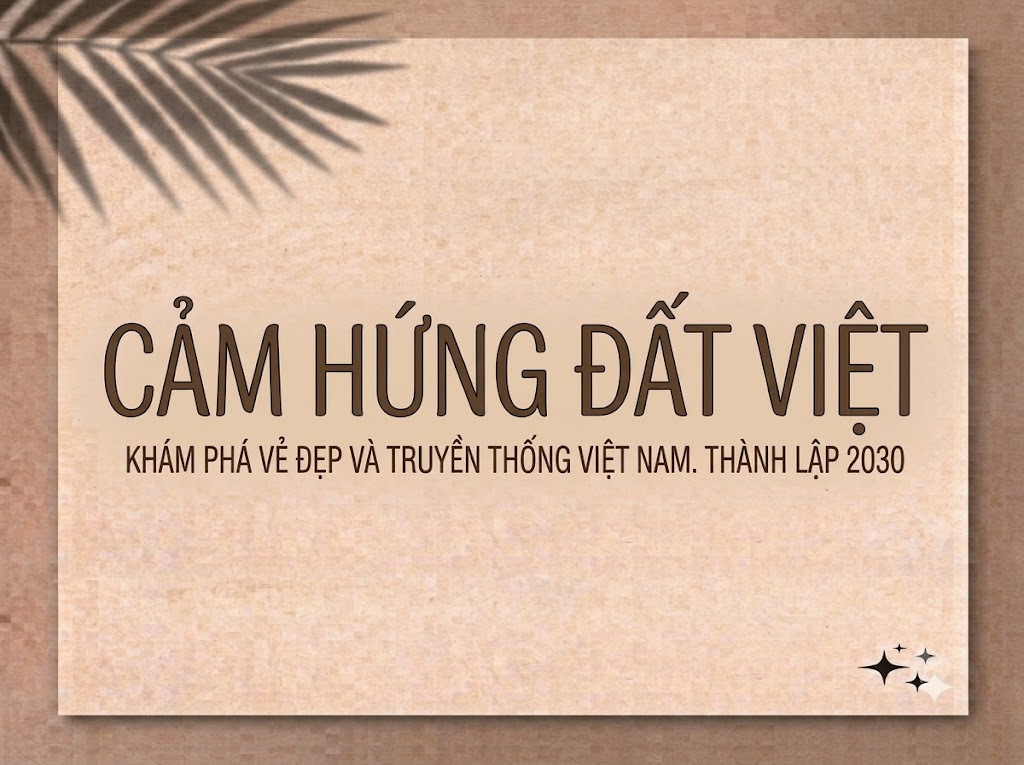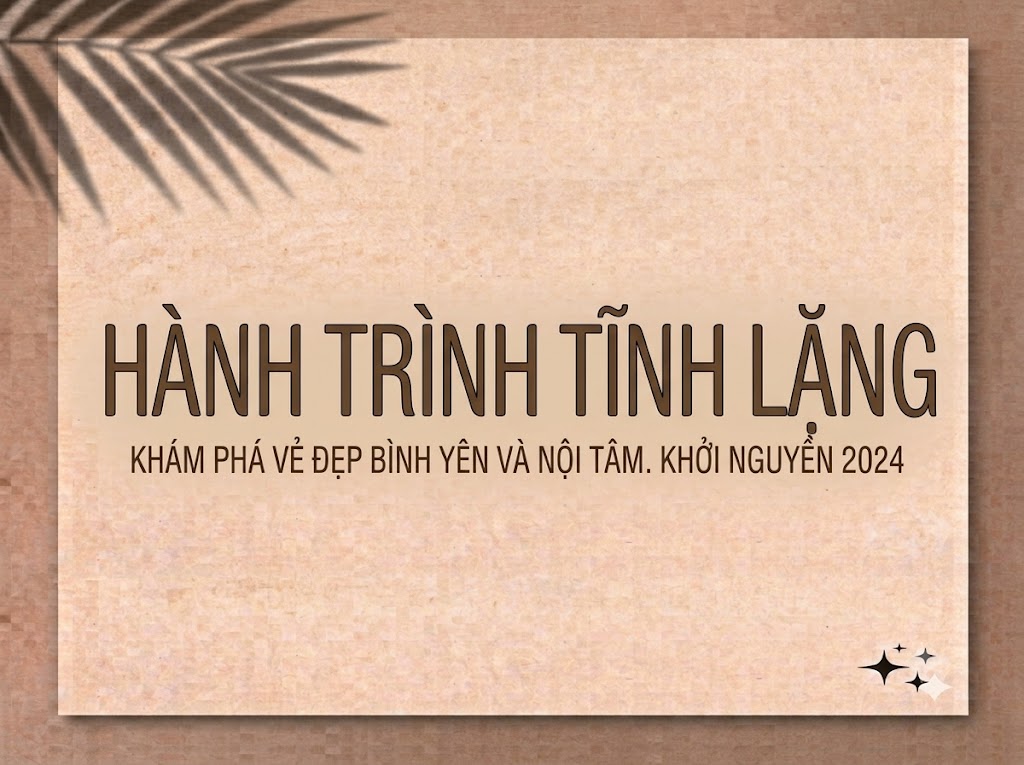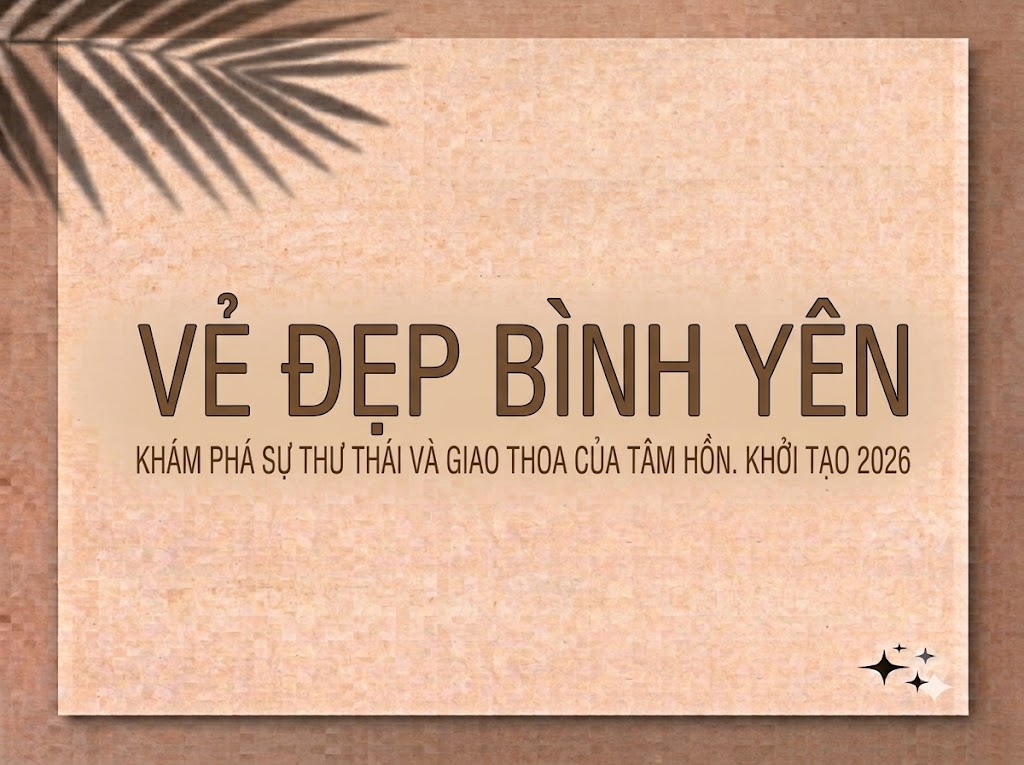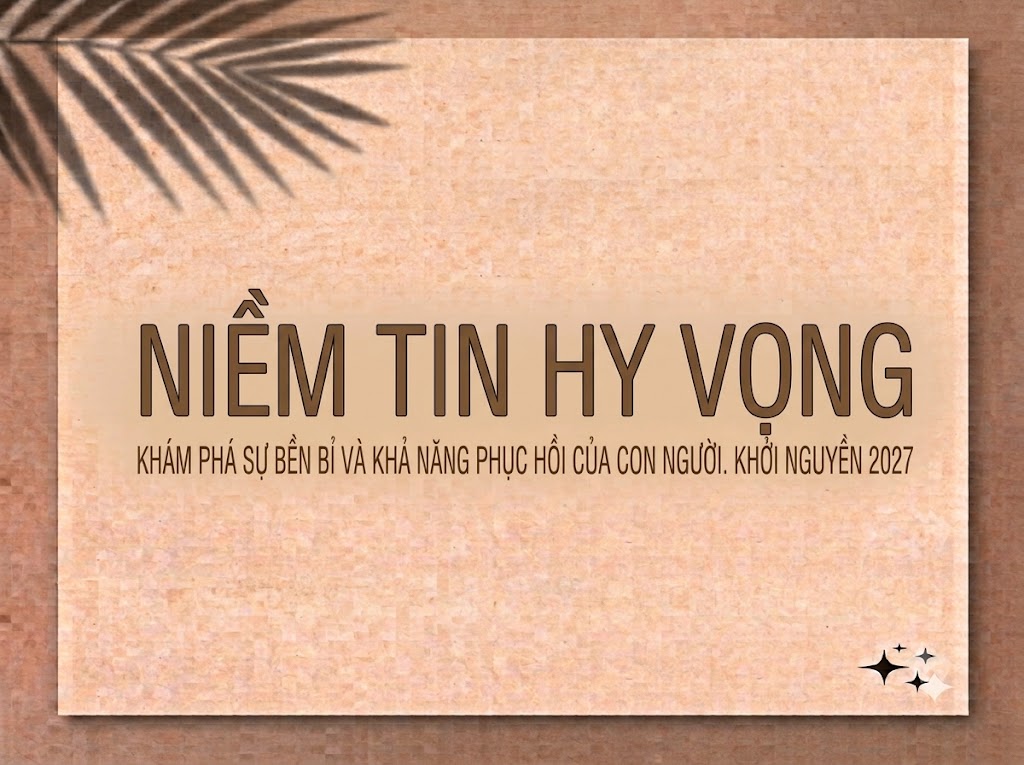
1FTV SS Magnetic
Trong thiết kế đồ họa hiện đại và sáng tạo nội dung số, việc lựa chọn một phông chữ không chân (sans-serif) tối giản nhưng có độ nhận diện cao luôn là yếu tố quyết định. Một phông chữ có cấu trúc hình học chuẩn mực, đường nét dứt khoát không chỉ giúp tối ưu hóa thị giác mà còn nâng cao trải nghiệm đọc của người xem trên các nền tảng di động.
Nếu bạn đang tìm kiếm một bộ font đa năng, mang tinh thần công nghệ, hiện đại và có khả năng hiển thị hoàn hảo từ các tiêu đề lớn đến phụ đề video ngắn, thì font 1FTV SS Magnetic chính là giải pháp không thể bỏ qua.
Giới thiệu về font 1FTV SS Magnetic
Font 1FTV SS Magnetic là một bộ chữ thuộc thể loại hiển thị không chân mang phong cách hình học đương đại (geometric sans-serif), hướng tới sự sạch sẽ, chuyên nghiệp và tối giản.
Nhờ cấu trúc kỹ thuật đồng bộ này, phông chữ có khả năng hiển thị vô cùng sắc nét trên các phần mềm đồ họa chuyên nghiệp mà không lo gặp phải lỗi răng cưa khi phóng lớn bố cục hay thiết kế các ấn phẩm khổ rộng.
Đặc điểm nổi bật của phong cách thiết kế SS Magnetic
Sức hút lớn nhất của font 1FTV SS Magnetic đến từ phom dáng đứng ngay ngắn, gọn gàng kết hợp với các tỷ lệ hình học cân đối và những đường vát cạnh vô cùng tinh tế:
Cấu trúc Geometric tối giản: Phông chữ sở hữu những đường bo tròn thông thoáng ở các ký tự như o, e, c, a, g, kết hợp với các nét thẳng vững chãi, tạo cảm giác vô cùng hiện đại và mang hơi hướng công nghệ.
Hỗ trợ hoa – thường đồng bộ: Bộ font hỗ trợ trọn vẹn cả hệ thống chữ cái viết hoa lẫn chữ viết thường, giúp các nhà thiết kế tự do sắp xếp bố cục nhằm mang lại một nhịp điệu đọc tự nhiên và thoáng mắt nhất cho người xem.
Độ dày nét vừa vặn (Medium/Bold): Nét chữ có độ dày lý tưởng, không quá thô cứng nhưng đủ sức nặng để làm nổi bật thông điệp truyền thông từ khoảng cách xa.
Để phông chữ vận hành hoàn hảo trên mọi hệ điều hành và phần mềm biên tập, phiên bản font 1FTV SS Magnetic đã trải qua quy trình xử lý thông số kỹ thuật nội tại vô cùng kỹ lưỡng:
Hệ thống khoảng cách chữ (kerning) và độ giãn dòng (tracking) đã được căn chỉnh chuẩn xác, giúp văn bản khi đứng cạnh nhau luôn đạt tỷ lệ vàng về mặt khoảng trống, không bị dính nét hay gây ngột ngạt cho người đọc.
Tích hợp đầy đủ dãy số từ 0-9 cùng hệ thống ký tự đặc biệt, dấu câu thông dụng (
Bản Việt hóa chuẩn chỉnh này đảm bảo các nhà sáng tạo có thể gõ nội dung tiếng Việt hoàn toàn mượt mà, tự nhiên mà không lo gặp phải tình trạng nhảy font hay lỗi hiển thị dấu câu khó chịu.
Hình ảnh demo thực tế của font 1FTV SS Magnetic
Kích thước nhỏ (12pt – 24pt): Nhờ cấu trúc chữ đứng ngay ngắn và khoảng hở chữ thông thoáng, các khối chữ viết thường vẫn hiển thị cực kỳ rõ ràng, sắc nét và dễ đọc ngay cả trên màn hình điện thoại di động cỡ nhỏ.
Kích thước lớn (36pt – 72pt): Đây là đất diễn lý tưởng nhất để font chữ phô diễn toàn bộ sự hiện đại, tạo hiệu ứng thị giác chuyên nghiệp, gọn gàng và ngăn nắp cho các dòng headline chính.
Ứng dụng của font SS Magnetic trong thiết kế đồ họa và làm video
Sở hữu nét cá tính thanh lịch, hiện đại và cấu trúc hoa – thường linh hoạt, font 1FTV SS Magnetic mở ra không gian ứng dụng vô cùng rộng lớn cho các dự án truyền thông và marketing hiện đại:
Làm tiêu đề và phụ đề video ngắn (TikTok, Reels, Shorts): Dáng chữ đứng, gọn gàng và thanh thoát cực kỳ hoàn hảo cho các khung hình dọc tỷ lệ 9:16. Độ rõ ràng của nét chữ giúp lời thoại phụ đề hiển thị một cách tự nhiên, cuốn hút người xem lướt feed dừng lại mà không che mất chủ thể chính của video.
Thiết kế ảnh thu nhỏ mạng xã hội (Thumbnail): Lựa chọn tuyệt vời cho các thumbnail YouTube, TikTok quảng cáo sản phẩm, nội dung chia sẻ kiến thức, mẹo marketing hoặc giáo dục nhằm tăng tỷ lệ nhấp chuột nhờ độ hiển thị trực diện, cực kỳ dễ đọc từ khoảng cách xa.
Banner và poster quảng cáo e-commerce, công nghệ: Hoàn hảo cho các poster giới thiệu sản phẩm công nghệ, đồ điện tử, thiết bị phần cứng, hoặc các chiến dịch marketing kỹ thuật số đòi hỏi sự tinh tế, súc tích và chuyên nghiệp.
Nhận diện thương hiệu phong cách tối giản: Phù hợp làm logo dạng chữ khối, biểu ngữ quảng cáo hoặc thiết kế nhãn mác cho các thương hiệu local brand, studio sáng tạo trẻ tuổi hướng tới sự hiện đại và bền vững.